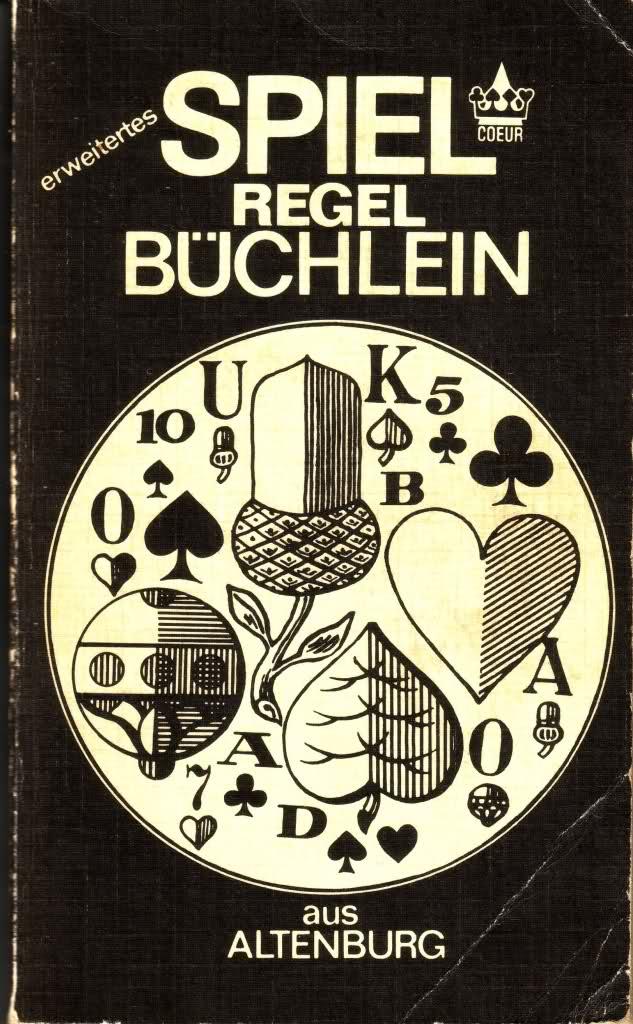
Das lustige Sommerloch-Ratespiel 2009
Klingt nach Impfstoff, Kanülen oder Infusionen.
Ich bin raus, da kenne ich mich nicht aus.
Es gehört zwar nicht zum Regelwerk, aber immerhin zum Usus, die erratenen Logos noch einmal im Ganzen einzustellen. :!:
Ich konnte nicht abwarten meins einzustellen, oder Foniq war zu langsam :D.
Aber vielleicht sollte dies mit in die Regeln aufgenommen werden.
• Der jeweilige Einsteller muss das vollständige Logo zur Auflösung zeigen.
B Braun Melsungen
pöh. das ging ja schnell. :o
war wohl zu einfach. :wink:
Es gehört zwar nicht zum Regelwerk, aber immerhin zum Usus, die erratenen Logos noch einmal im Ganzen einzustellen. :!:
B Braun Melsungen
pöh. das ging ja schnell. :o
war wohl zu einfach. :wink:
Naja, die haben Ihren Sitz eine Stadt weiter. ;)
Ich wäre übrigens ohne dein Geschriebenes nicht drauf gekommen! Habe das Logo überhaupt nicht so filigran im Kopf!
Es gehört zwar nicht zum Regelwerk, aber immerhin zum Usus, die erratenen Logos noch einmal im Ganzen einzustellen. :!:
deutsch, leute! deutsche logos! :peng:
Oh, oh. Und dann noch diese Präferenz für die Tannenberg. Müssen wir uns Sorgen um Dich machen? 8)
deutsch, leute! deutsche logos! :peng:
Oh, oh. Und dann noch diese Präferenz für die Tannenberg. Müssen wir uns Sorgen um Dich machen? 8)
Ach, gebrochene Schriften sind per se nichts Böses :D.
@RobertMichael: Musst du gleich so rumschießen? Du hast ja selbst geschrieben, dass es auch ein bekanntes ausländisches Unternehmen sein darf, und Dreamworks sehe ich als bekannt an.
Zum Glück ist mein Unternehmen ein deutsches :P.
bekannt ist was ICH kenne. ;) schade das deutsch kein R hat.
dass könnte man so schön rollen. tannenberrrrg! TANNENBERRRG!
WEITERRRMACHEN, MAAARRRSCH! LOGO RRRRATEN!
Naja, die haben Ihren Sitz eine Stadt weiter. ;)
Ich wäre übrigens ohne dein Geschriebenes nicht drauf gekommen! Habe das Logo überhaupt nicht so filigran im Kopf!
tja. da sieht man mal wieder, wie man im vermeintlich bekannten doch immer wieder neues entdecken kann.
auch der slogan "sharing expertise" würde sehr gut zu diesem forum hier passen.
WEITERRRMACHEN, MAAARRRSCH! LOGO RRRRATEN!
scho recht. I rad ja scho.
Ehemaliges Logo, eingesetzt in der DDR, im weiteren Sinne Papierverarbeitung.
Mal so ins Blaue hinein:
VEB Papier- und Kartonwerke Schwedt?
Ehemaliges Logo, eingesetzt in der DDR, im weiteren Sinne Papierverarbeitung.
Mal so ins Blaue hinein:
VEB Papier- und Kartonwerke Schwedt?
Nein, liegt etwas weiter südlich … :D
Ich betone noch einmal im weiteren Sinne. :wink:
... dann vielleicht ein Verlag?
Ich betone noch einmal im weiteren Sinne. :wink:
... dann vielleicht ein Verlag?
Nein, eigentlich nicht.
So was wie eine Buchbinderinnung?
Nein.
Denkt mal an den Wald, aber denkt um ein paar Ecken. :D
wenn ich an wald & wirtschaft denken soll, denke ich erst mal an forstwirtschaft. das wäre aber um keine ecke gedacht, sondern direkt.
um eine ecke wäre so etwas wie holzverarbeitung/möbelindustrie.
um zwei ecken zellstoffindustrie, papierherstellung, kartonagen, usw.
um drei ecken: druck- und verlagswesen.
vier ecken? ja was weiss ich. die rennpappe ... der trabbi? isses aber auch nicht, da dein ausschnitt nicht zum VEB sachensring-logo passt.
noch ein kleiner tipp vielleicht?
Ich löse den Tipp mit dem Wald mal auf: Eicheln …
Geht mal etwas spielerisch an die Sache heran. :D
meinst du vielleicht ASS Skatkarten aus Altenburg. Ich kenn da nur das aktuelle Logo :?
(falls es richtig sein sollte, darf für mich der schnellste Nachleger nachlegen, ausgenommen natürlich dem Vorleger. Ich muss weg)
meinst du vielleicht ASS Skatkarten aus Altenburg. Ich kenn da nur das aktuelle Logo :?
(falls es richtig sein sollte, darf für mich der schnellste Nachleger nachlegen, ausgenommen natürlich dem Vorleger. Ich muss weg)
:party:
Genau, ich meine den
VEB Altenburger Spielkartenfabrik, Altenburg Thüringen:
i6m58l.jpg
Heute im belgischen Konzern Carta mundi eingebettet.
Der heutige Name ist ASS Altenburger (ASS = Altenburger und Stralsunder Spielkartenfabriken)
Hatte man sich nach der Wende noch ein dem früherem Logo ähnliches genommen, mit diesem firmierte eine westdeutsche Firma aus Steinenbronn, die sich auch ASS nannte, und das Vorkriegslogo übernommen hatte. Nach der Wende wurde ja dann alles wiederzusammengefügt und die Produktion nach Altenburg verlegt.
Seit neustem ist das Logo aber an das des Mutterkonzerns angepasst. :evil: (Vorher sah es besser aus!)
Um den Wald noch weiter aufzuschlüsseln: Wald ? Eicheln, Grün, Rot, Schellen ? Farben des Deutschen Bildes ? Spielkarten ? Ostdeutschland ? Altenburg.
Logisch, oder? :D